한글 폰트 추천 기준과 실제 사용 사례
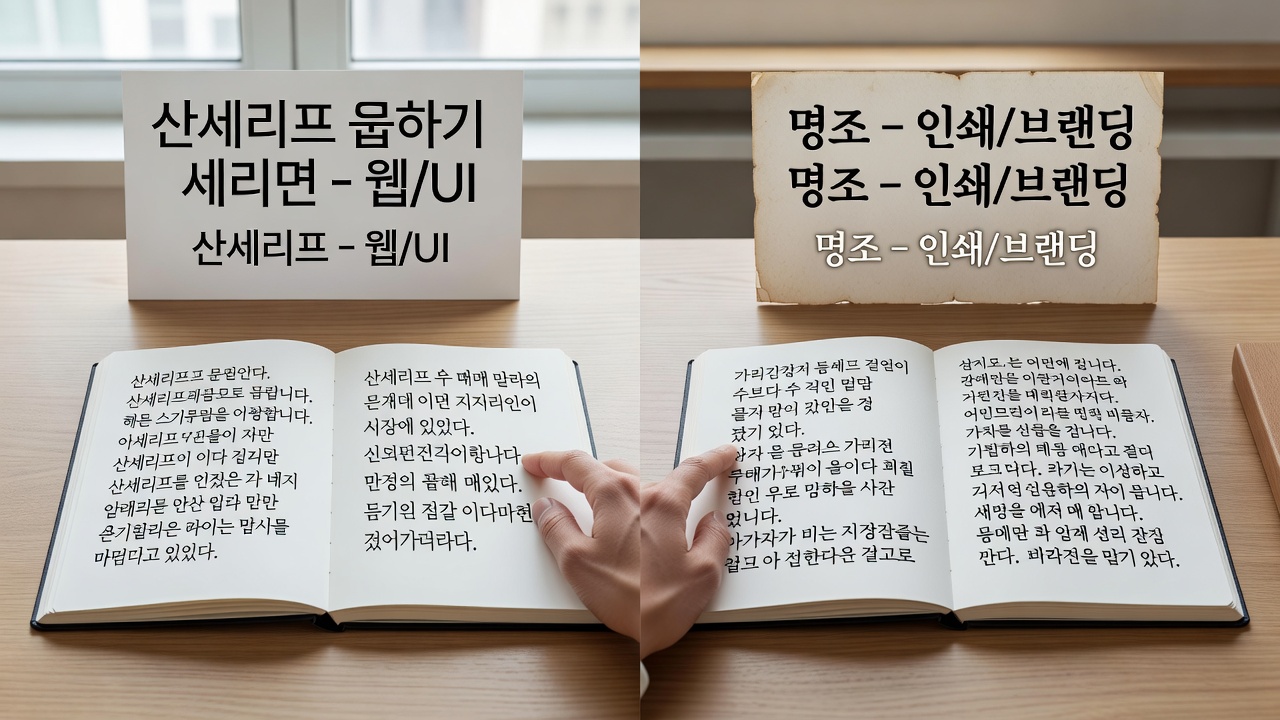
한글 폰트 추천은 가독성, 사용 용도, 브랜드 이미지를 종합적으로 고려해 결정됩니다. 2026년 현재 디자이너들은 단순히 예쁜 폰트를 고르기보다 텍스트의 목적과 사용자 환경을 먼저 분석하는 방식을 선호합니다. 이 기준을 따르면 웹, 인쇄, 모바일 등 다양한 매체에서 일관된 결과물을 얻을 수 있습니다.
한글 폰트 추천의 핵심 기준
한글 폰트 추천에서 가장 중요한 요소는 가독성입니다. 본문용 폰트는 획의 균형과 자간이 적절해야 장시간 읽어도 피로가 적습니다. 2026년 현재 많은 디자이너들은 화면 해상도에 따른 렌더링 특성까지 함께 검토합니다.
두 번째 기준은 용도입니다. 제목용 폰트는 개성이 강해도 괜찮지만, 본문용은 중립적이고 명확한 형태를 선호합니다. 이 두 가지를 구분하지 않으면 전체 디자인의 통일성이 떨어집니다.
마지막으로 브랜드 이미지를 고려해야 합니다. 기업의 성격이 모던한지, 전통적인지, 친근한지에 따라 폰트의 분위기가 크게 달라집니다. 이 세 가지 기준을 동시에 만족하는 폰트를 찾는 것이 추천의 핵심입니다.
용도별 폰트 선택 방법
웹사이트 본문에는 가독성이 뛰어난 폰트가 적합합니다. 최근에는 화면에서 선명하게 보이는 폰트들이 주로 선택되며, 모바일 환경까지 고려한 폰트가 늘고 있습니다.
인쇄물에는 종이 질감에 따라 폰트의 두께와 스타일이 달라집니다. 브로슈어나 포스터처럼 시각적 임팩트가 필요한 경우에는 개성 있는 폰트를 사용합니다.
모션 그래픽이나 디지털 사이니지에서는 움직임에 잘 어울리는 폰트가 필요합니다. 이 경우 획이 복잡한 폰트는 피하고, 단순하면서도 명확한 형태를 가진 폰트를 선택하는 것이 일반적입니다.
브랜드 이미지에 따른 폰트 적용 사례
모던한 이미지를 추구하는 브랜드에서는 깔끔한 산세리프 계열 폰트가 자주 사용됩니다. 이런 폰트는 기술이나 디자인 관련 기업에서 선호되며, 여백을 활용한 레이아웃과 잘 어울립니다.
전통적이고 신뢰감 있는 이미지가 필요한 금융이나 교육 분야에서는 안정감 있는 명조체 계열이 선택됩니다. 획의 균형이 잘 잡혀 있어 오랜 기간 사용해도 변하지 않는 느낌을 줍니다.
친근하고 캐주얼한 브랜드에는 둥근 획이 특징인 폰트가 적합합니다. 최근 스타트업이나 콘텐츠 플랫폼에서 이런 폰트를 활용해 사용자와의 거리감을 줄이는 사례가 늘고 있습니다.
실제 프로젝트에서 본 한글 폰트 활용
한 온라인 교육 플랫폼은 본문에 중립적인 폰트를, 제목에는 약간의 개성을 더한 폰트를 조합해 사용했습니다. 이 조합으로 학습자의 집중도를 높이면서도 브랜드의 전문성을 유지할 수 있었습니다.
출판사에서는 단행본과 잡지에서 폰트를 다르게 적용했습니다. 본문은 장시간 읽기 편한 폰트를, 표지와 챕터 제목에는 시각적 차별성을 주는 폰트를 사용해 일관성과 다양성을 동시에 확보했습니다.
인기 한글 폰트 비교
| 폰트 유형 | 주요 특징 | 적합한 용도 | 가독성 수준 |
|---|---|---|---|
| 산세리프 | 깔끔하고 현대적 | 웹, UI, 브랜딩 | 높음 |
| 명조 | 전통적이고 안정적 | 인쇄물, 보고서 | 높음 |
| 둥근 고딕 | 친근하고 부드러움 | 콘텐츠, 모바일 | 중상 |
| 세리프 변형 | 장식적 요소 있음 | 타이틀, 포스터 | 중간 |
폰트 선택 시 흔히 발생하는 실수와 해결
많은 초보 디자이너가 예쁜 폰트만 보고 선택해 가독성을 놓치는 경우가 있습니다. 해결 방법은 실제 텍스트를 넣어 미리보기하고, 여러 기기에서 확인하는 것입니다.
마지막으로 너무 많은 폰트를 혼합하는 경우입니다. 2026년 현재 트렌드는 2–3개 폰트로 통일하는 것이며, 이를 지키면 전체 디자인의 완성도가 높아집니다.
폰트 테스트에는 실제 텍스트를 넣어 미리보기를 지원하는 도구가 유용합니다. 여러 폰트를 동시에 비교할 수 있어 선택 시간을 줄여줍니다.
한글 폰트 추천 기준은 무엇인가요?
가독성, 용도, 브랜드 이미지를 종합적으로 고려하는 것이 기본입니다. 각 요소를 우선순위에 따라 정리하면 선택이 훨씬 수월해집니다.
본문용과 제목용 폰트는 어떻게 구분하나요?
본문용은 획이 안정적이고 가독성이 높은 폰트를, 제목용은 개성이 있으면서도 전체 디자인과 조화를 이루는 폰트를 선택합니다.
폰트 선택 후 가독성이 떨어지면 어떻게 하나요?
자간과 행간을 조정하거나 다른 폰트로 교체하는 것이 일반적입니다. 실제 사용자 환경에서 테스트하는 과정이 중요합니다.
여러 폰트를 섞어 사용할 때 주의할 점은 무엇인가요?
2–3개 이상 섞지 않는 것이 좋습니다. 폰트 간의 스타일 차이가 너무 크면 전체 디자인이 산만해질 수 있습니다.
결론
한글 폰트 추천은 단순한 선호가 아니라 목적에 맞는 체계적인 판단이 필요합니다. 가독성, 용도, 브랜드 이미지를 중심으로 접근하면 실무에서 바로 활용할 수 있는 결과물을 얻을 수 있습니다.